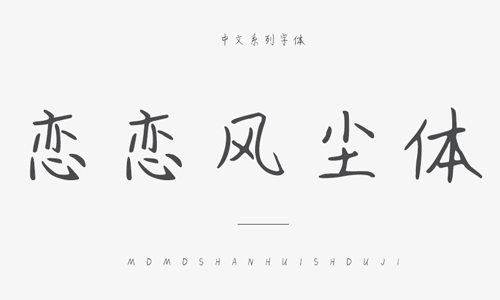
戀戀風塵體字體是思雨字庫中一款非常不錯的硬筆手寫字體,“迷戀一種情懷,想念一段時光,給我一種寵愛,忘卻一生煩憂。——戀戀風塵體”,本字體是在國家標準簡體字庫GB2312所包含6763漢字的基礎上,又增加了近200常用字,已經(jīng)覆蓋了大陸99.75%的漢字使用頻率,足以滿足日常需求。歡迎大家前來下載。